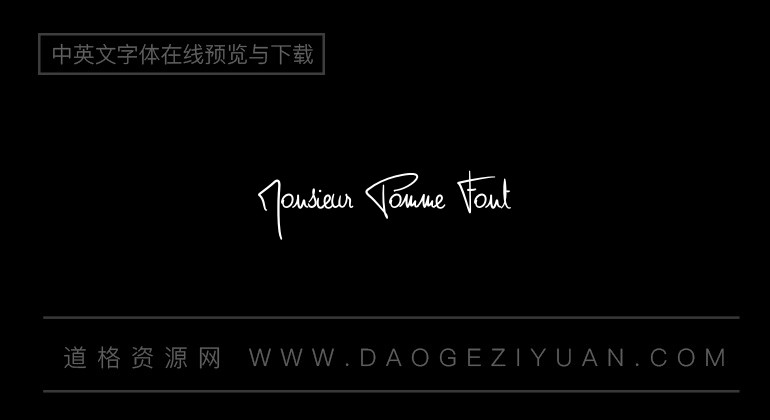
Monsieur Pomme Font
Monsieur Pomme Font是一种手写风格的字体。它由法国设计师Monsieur Pomme于2012年设计。这个字体的特点是流畅的线条和有趣的字母形状。字母看起来像是手写的,具有一定的艺术感和个性。 Monsieur Pomme Font适用于多种设计场合,比如书籍封面、海报、包装设计和标志设计等。它的设计感和特殊的风格可以吸引人们的注意力,使设计作品与众不同。 该字体提供多种字形变化和语言支持,可以在不同的平台和设备上使用。此外,该字体还有许多配套的图形元素和图案,可以用于更加丰富的排版设计。
Monsieur Pomme Font是一款非常不错的手写艺术字体,具有很好的视觉感,适合于文化类的宣传设计、商业类品牌的广告和产品包装设计以及个性化文字排版等较多场景。